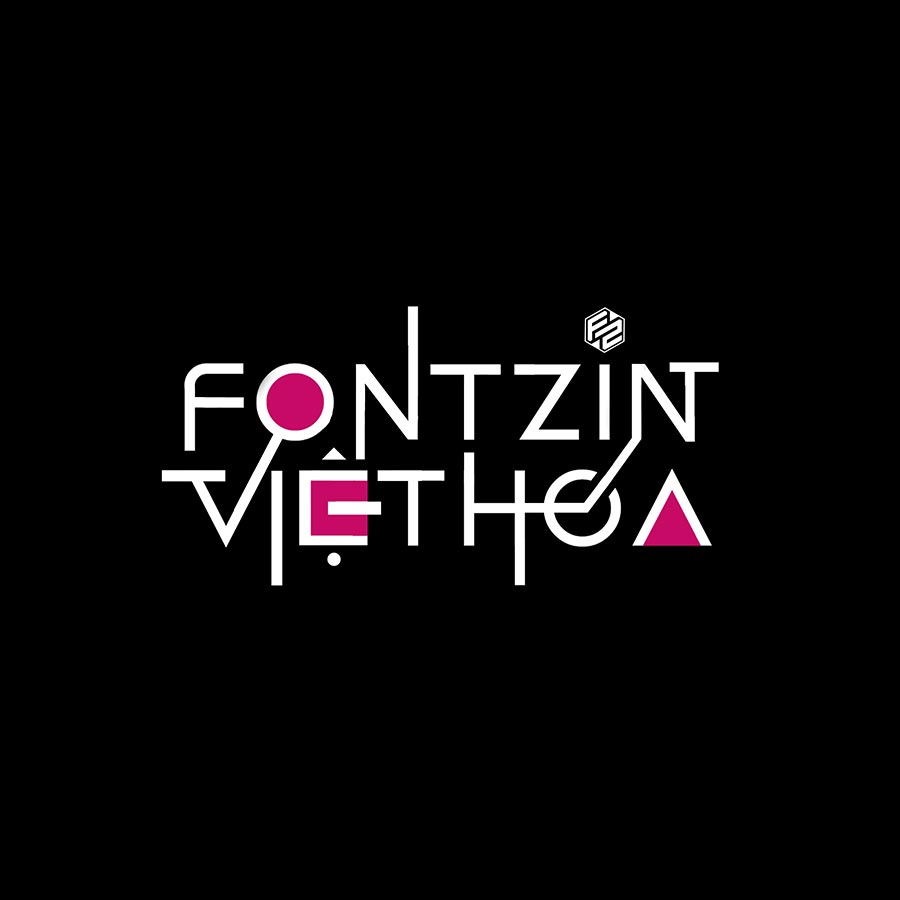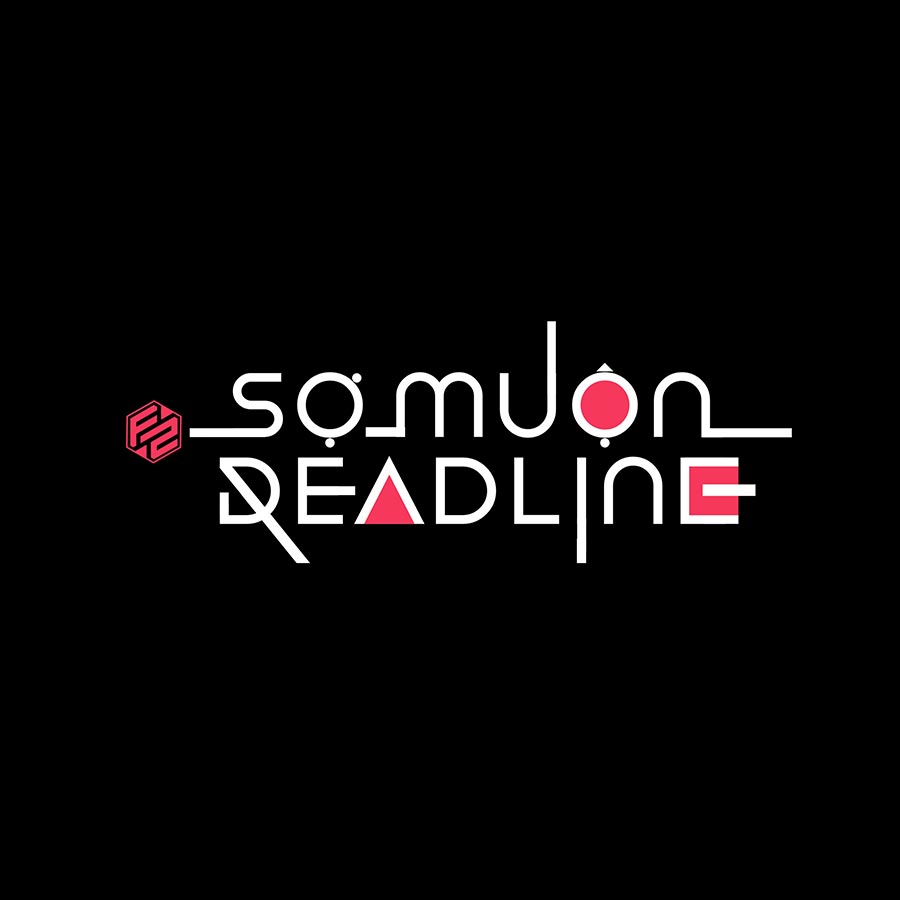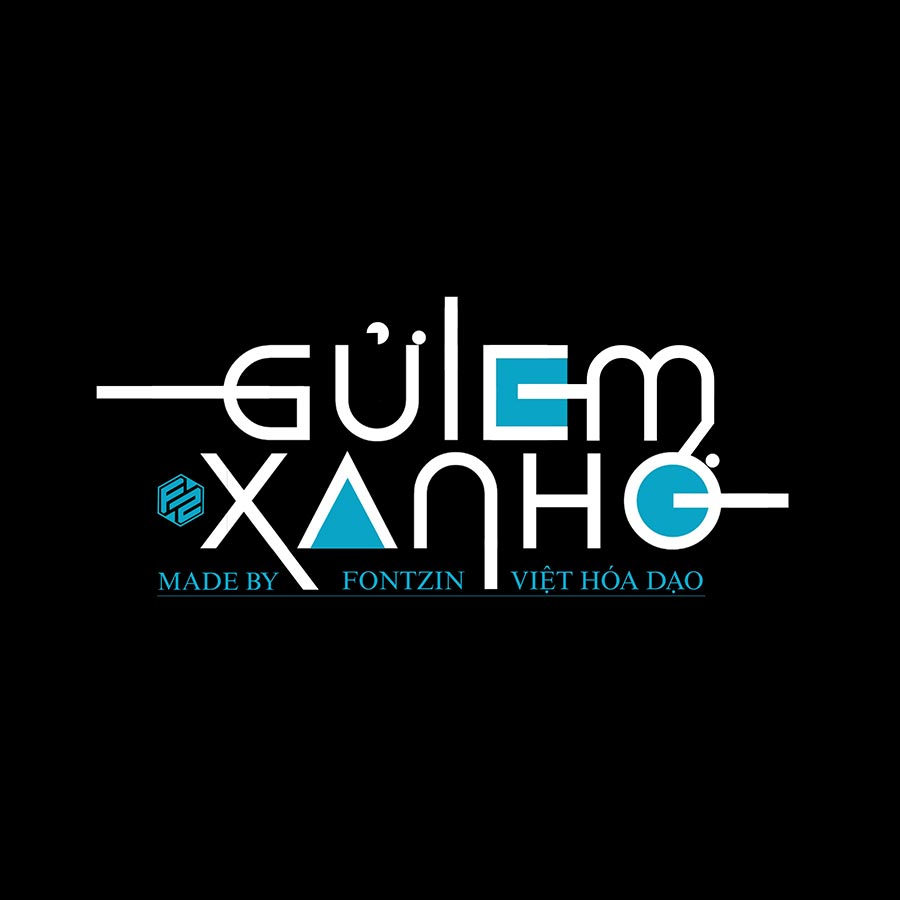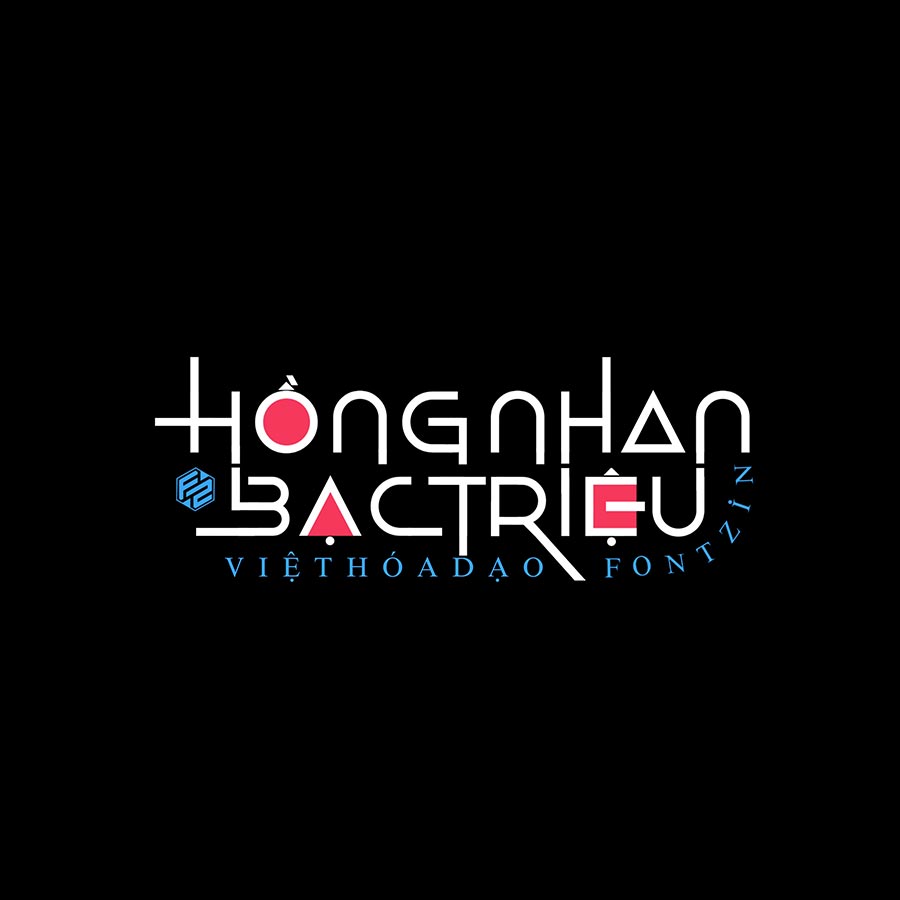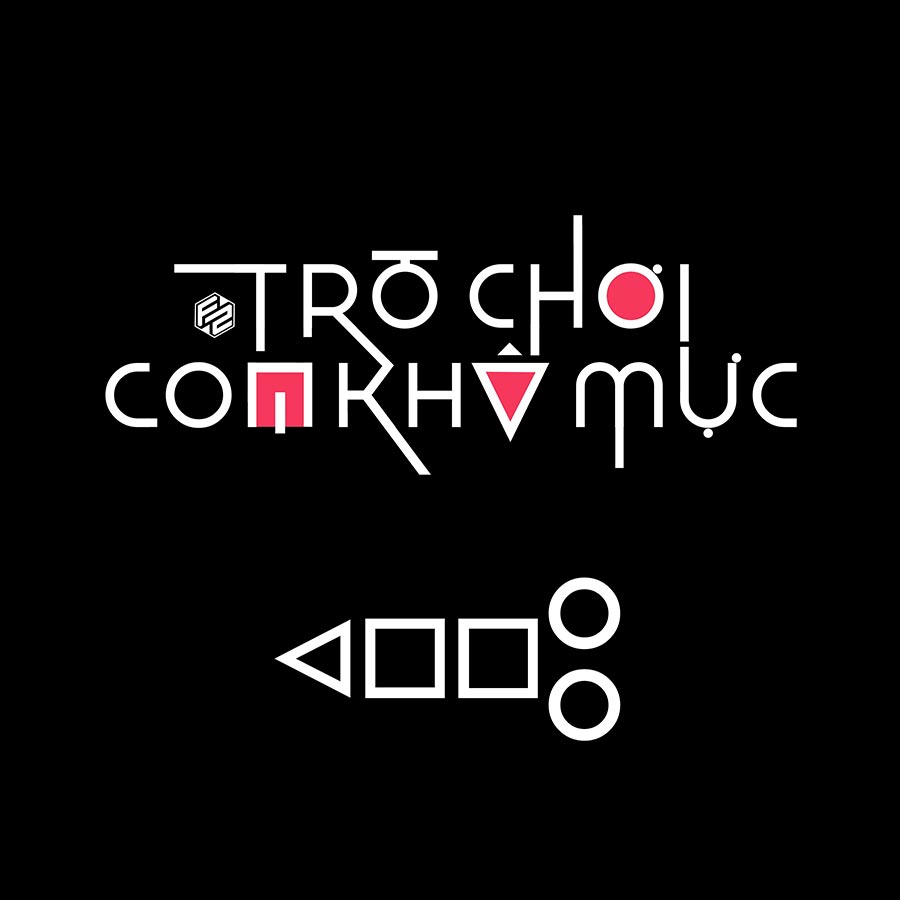
Chia Sẻ Miễn Phí Font Chữ Việt hóa SquidGame - Trò Chơi Con Mực Tác Giả FontZin (ttf)
Nếu bạn là một nhà thiết kế đồ họa hoặc đơn giản là một người yêu thích nghệ thuật chữ, chắc chắn bạn không thể bỏ qua font chữ Việt hóa Squid Game – một tác phẩm độc đáo được tạo ra bởi tác giả FontZin. Đây là một bộ font miễn phí được chia sẻ bởi trang web sadesign.vn, mang đến cơ hội tuyệt vời để bạn thỏa sức sáng tạo trong các dự án thiết kế của mình.
Về Font Chữ Squid Game
Font chữ Squid Game được lấy cảm hứng từ bộ phim nổi tiếng cùng tên của Hàn Quốc. Với phong cách thiết kế hiện đại, mạnh mẽ nhưng không kém phần tinh tế, font chữ này đã nhanh chóng trở thành một xu hướng trong cộng đồng thiết kế. Điểm đặc biệt của phiên bản Việt hóa là khả năng hỗ trợ đầy đủ các ký tự tiếng Việt, giúp người dùng dễ dàng ứng dụng trong các dự án mang tính địa phương.
Đặc Điểm Nổi Bật
- Thiết kế độc đáo: Font chữ mang đậm dấu ấn của bộ phim Squid Game, với các đường nét tối giản nhưng đầy cá tính.
- Hỗ trợ tiếng Việt: Phiên bản Việt hóa đảm bảo hiển thị tốt các dấu và ký tự đặc trưng của ngôn ngữ Việt Nam.
- Ứng dụng linh hoạt: Phù hợp cho nhiều loại dự án như thiết kế poster, banner, bìa sách, hoặc các sản phẩm truyền thông quảng cáo.
Lợi Ích Khi Sử Dụng Font Việt Hóa
Việc sử dụng font chữ Việt hóa không chỉ giúp bạn tiết kiệm thời gian chỉnh sửa mà còn đảm bảo tính thẩm mỹ và chuyên nghiệp cho các sản phẩm thiết kế. Đặc biệt, với font Squid Game, bạn có thể dễ dàng tạo nên những tác phẩm độc đáo và thu hút sự chú ý từ người xem.
Kết Luận